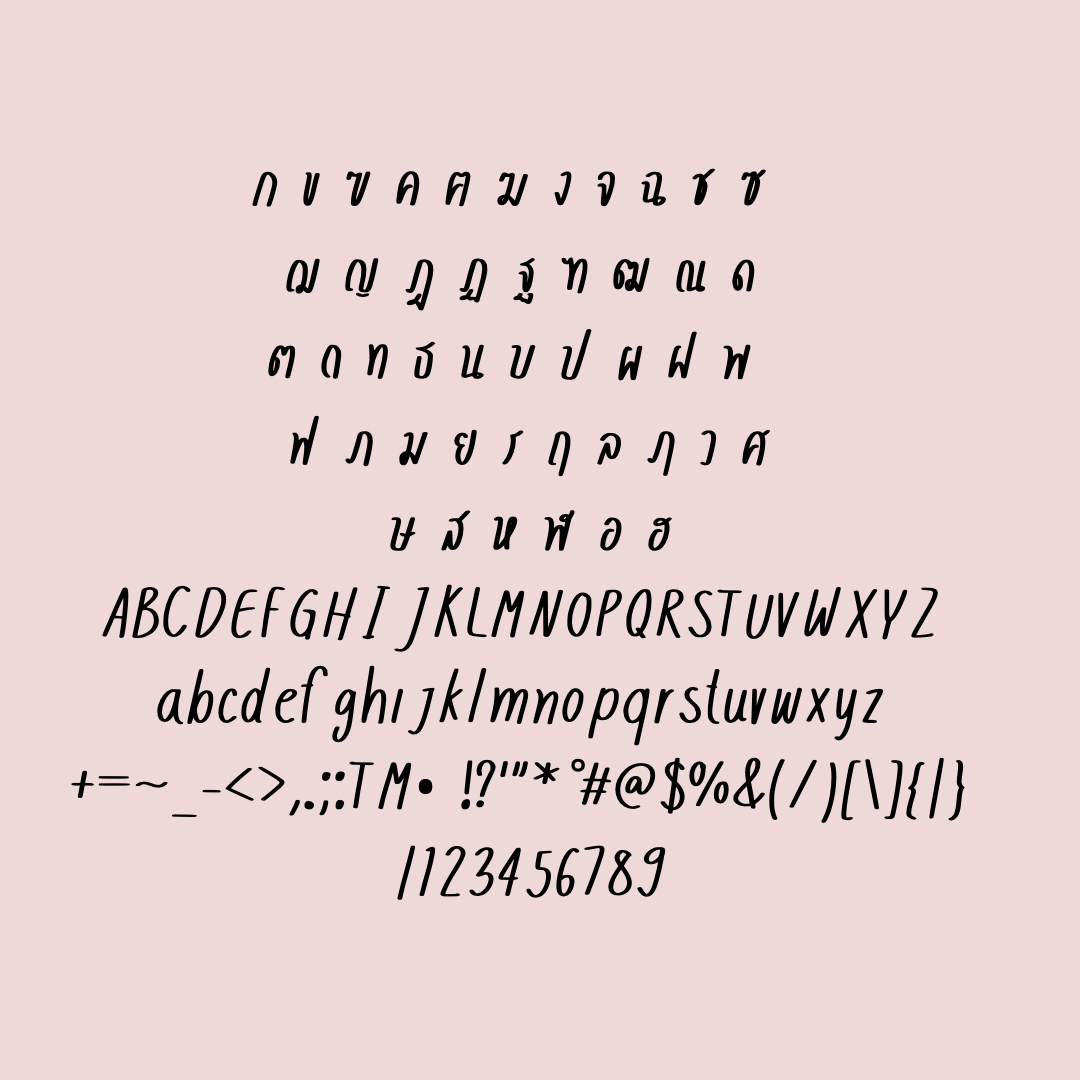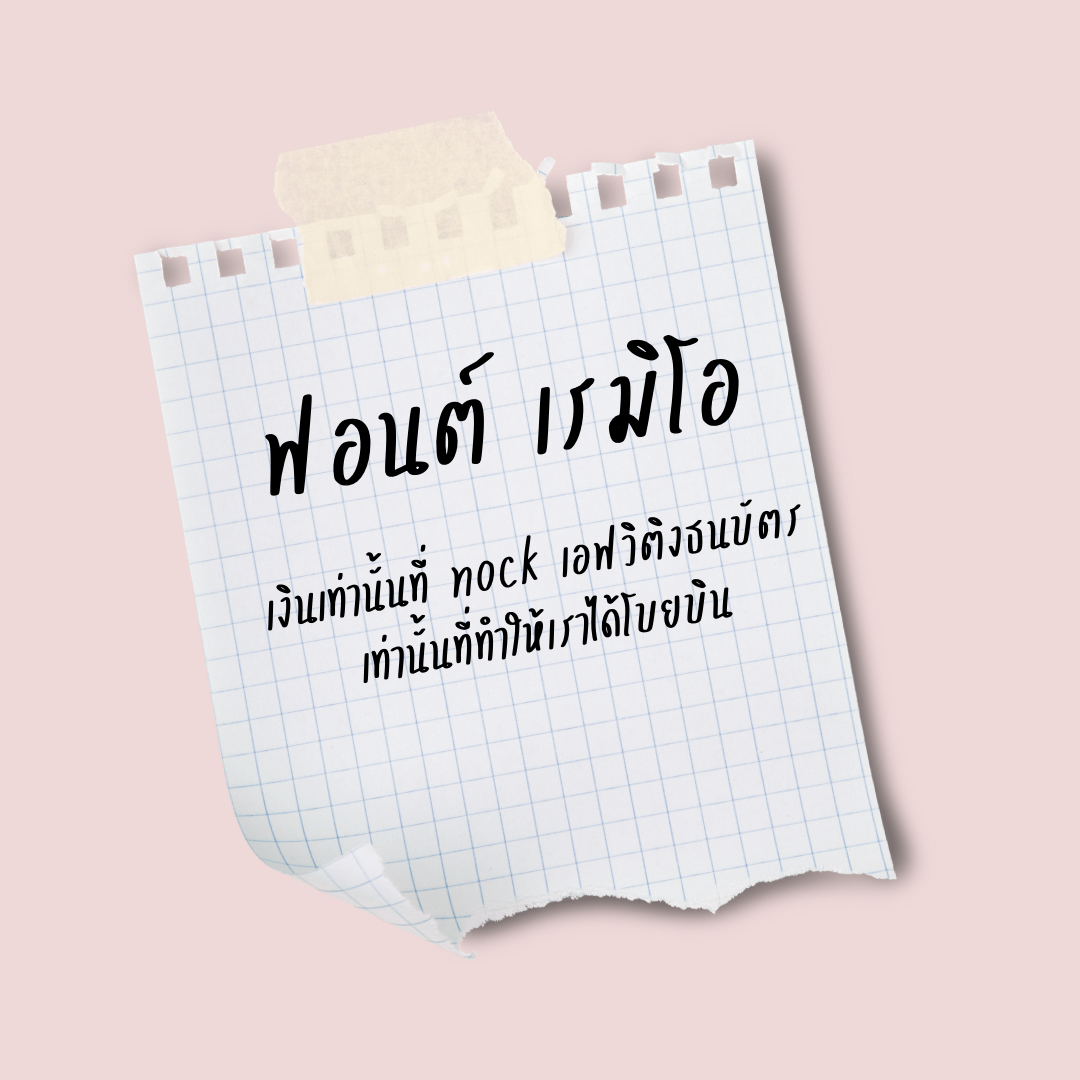
เรมีโอ (Remio)
ฟอนต์ เรมีโอ(Remio) ฟอนต์ที่มีเอกลักษณ์ ใช้ทำงานสไตล์น่ารักๆ จดโน้ต หรือจะทำแฟลชการ์ดก็ดูดี แจกฟรีไปเลยเวอร์ชันทดลอง : แบบปกติ 1 น้ำหนัก ใช้ได้เฉพาะแบบส่วนตัว เช่น ใช้ในการศึกษา ใช้จด ใช้ตกแต่งสมุดโน้ตตัวเอง